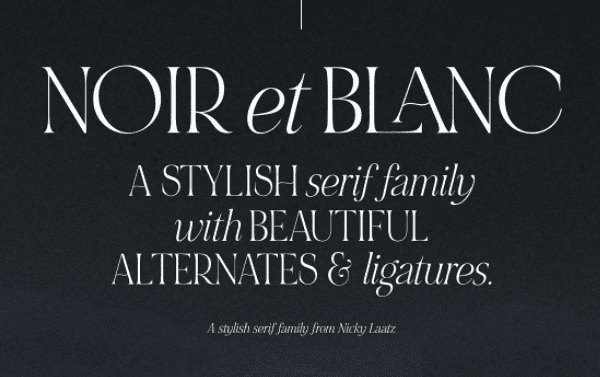
Как драматично сочетаются черное и белое - поприветствуйте "NOIR et BLANC" - стильное семейство засечек с красивыми лигатурами и чередованиями. Созданные для гармоничного использования, резкий контраст смелых и сладострастных заглавных букв обычного серифа прекрасно сочетается с изящными и знойными строчными буквами его курсивного аналога.
Добавьте интерес, добавив красивые лигатуры и чередования, чтобы сделать вашу типографику по-настоящему уникальной.
NOIR et BLANC выпускается в трех вариантах, отличающихся друг от друга по весу, благодаря чему шрифт хорошо смотрится как на больших, так и на малых размерах, а также на светлых и темных фонах.